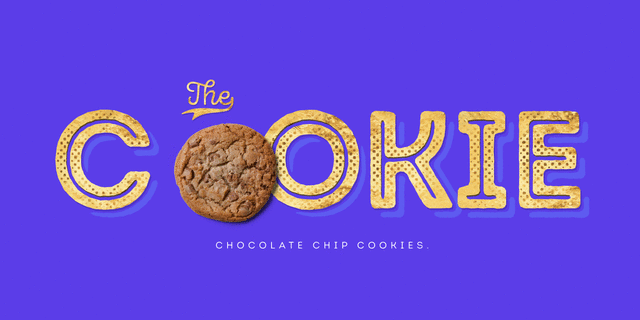
Бесплатное начертание одной из крупнейших шрифтовых систем в мире Интро Раст, включающей 214 начертаний. Это огрубленная текстурная версия известного шрифта Интро. Система Интро Раст включает 4 семейства: Intro Rust, Intro Script, Intro Head и Intro Goodies. Она может применяться для создания почти всех видов дизайнерской продукции от полиграфии до веб-дизайна. Просто используйте воображение и ваши проекты станут более живыми, благодаря шрифтам системы Интро Раст. Хотите сделать поздравительную открытку или дизайн упаковки или даже айдентику? Смело экспериментируйте с паттернами и рисунками, рукописными версиями или теми классными начертаниями с точками и получайте современный успешный дизайнерский проект. Шрифт разработан Светославом Симовым, Ани Петровой и Радомиром Тинковым в 2015 году и выпущен фирмой Фонтфабрик. http://www.fontfabric.com/intro-rust/
хипстерский, винтажный, бытовой, грубый, заметный, броский, статичный, убедительный, твердый, надежный, консервативный, честный, ветхий, старый, добротный, крепкий, железный, деревянный, доступный, экологичный, эффектный, зеленый, натуральный, природный, теплый, ламповый, мотивирующий, оригинальный, выразительный, модный, качественный, городской, суровый, крафтовый, осенний, горячий, огненный